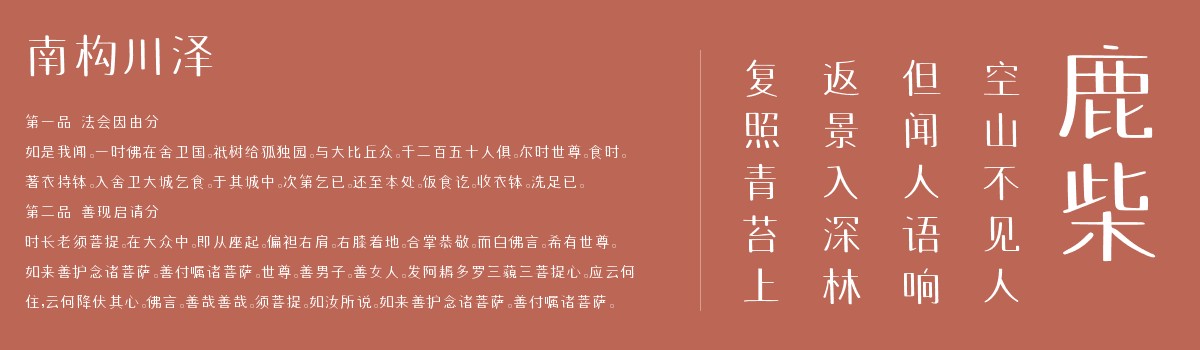
南构川泽
南构川泽是一款由字体家AI神笔造字生成的艺术字体,此字体横画纤细、竖画劲挺,粗细对比鲜明却不显突兀。笔画起收处有规整顿笔,如横画收笔带利落小三角,竖画起笔呈方头,刚劲中透着克制。整体结构方正,中宫紧凑,笔画穿插避让和谐,无松散之感。撇捺舒展却不过分张扬,弧度平缓,兼具传统韵味与现代简洁,端庄清晰,似稳健君子,于规整中见精致,于刚直中显温润。适合用于一些广告标题、平面文案、海报标题、网页广告用字的编辑。